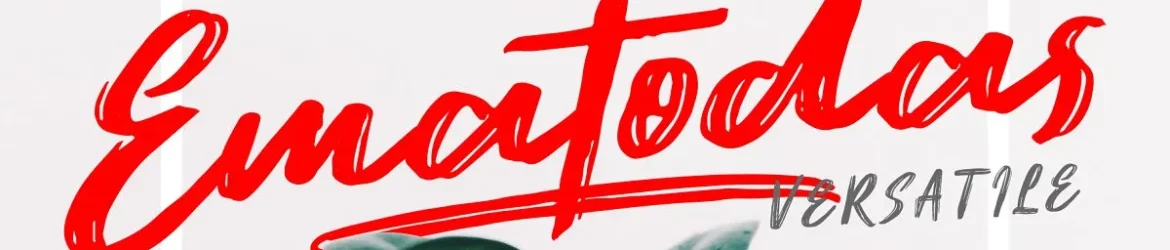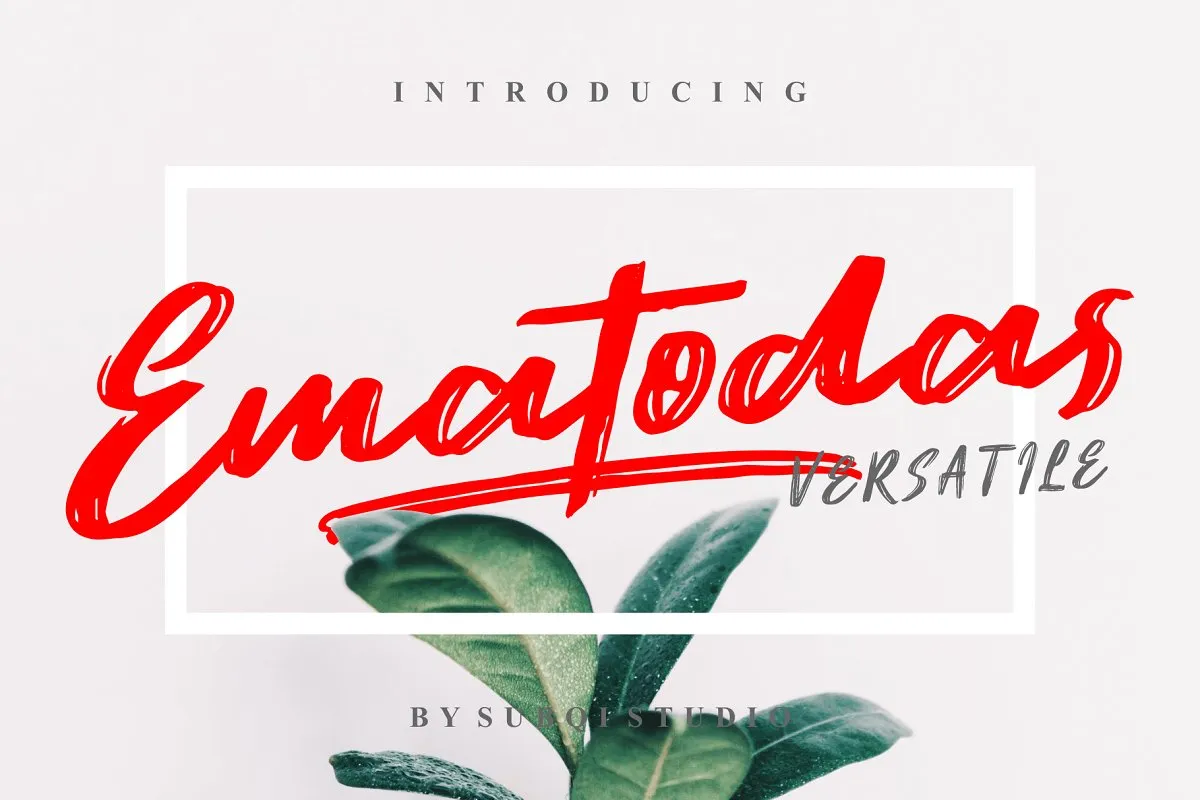
Ematodas Brush Font – Fonte Grátis
Ematodas Brush Font
A Ematodas Brush Font é uma nova tipografia bold criada com a técnica do traçado à mão livre, ou seja, com a sensação de um pincel seca na tela. A designer 0001themes introduziu este novo recurso gráfico que traz textura de pincelagem seca que permite sentir o peso da letra em cada caractere. Com sua versatilidade, esta fonte oferece uma experiência única para designers profissionais e amadores, permitindo experimentar seu uso na maioria dos capítulos com letras maiores do tipo All Caps. Esta font é um verdadeiro trunfo para qualquer projeto de design, transformando textos normais em criações memoráveis. Com o Ematodas Font, os designers podem criar designs que chamam a atenção e se destacam no mercado da gráfica.